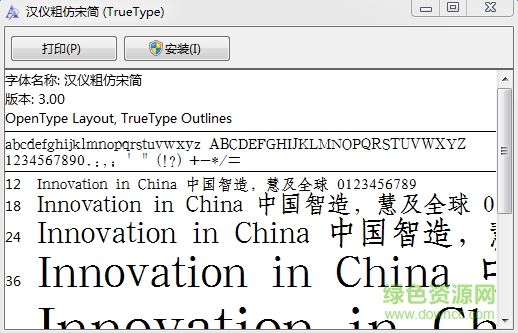
hyd4gj字體是一款筆畫(huà)較粗的漢儀仿宋體,該字體線(xiàn)條較銳利,結(jié)構(gòu)工整規(guī)范,外形雅致美觀,且?guī)в凶帜_,也屬于一種襯線(xiàn)字體,喜歡的小伙伴快來(lái)下載吧!
仿宋是印刷字體的一種,仿照宋版書(shū)上所刻的字體,筆畫(huà)粗細(xì)均勻,有長(zhǎng)、方、扁三體,也叫仿宋體,仿宋字。仿宋體是仿照宋版書(shū)的字體演變而來(lái)的,但仿宋的結(jié)構(gòu)特征決定了它必須有一定的傾斜。
宋體字形較方正,基本可以同時(shí)滿(mǎn)足橫排和直排的需要;
而仿宋的結(jié)構(gòu)特征決定了它必須有一定的傾斜,一旦被調(diào)正會(huì)十分呆板。